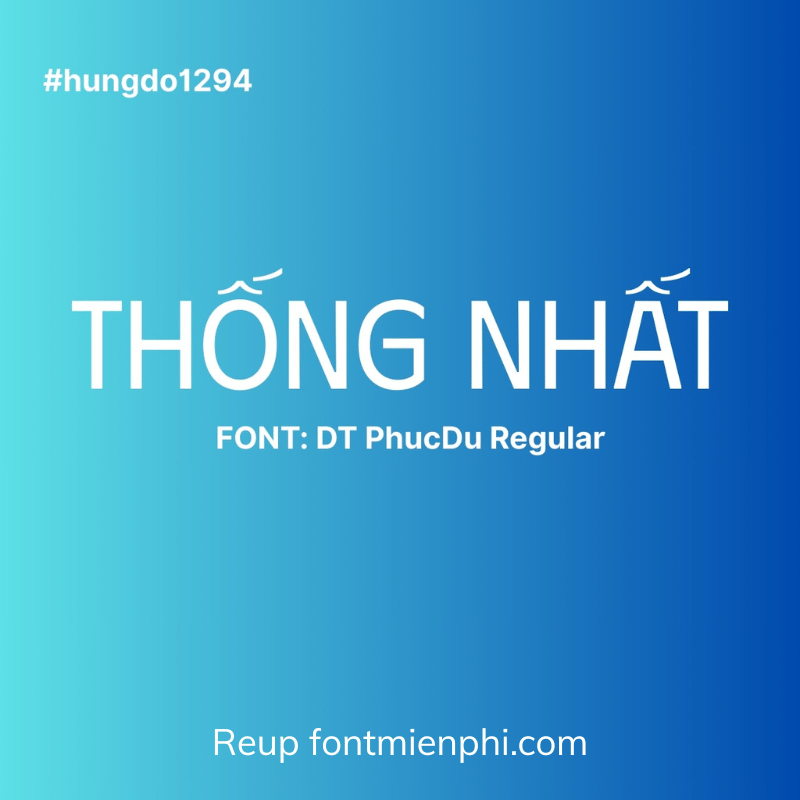
Mô tả SDT Phudu Việt Hóa – Font Đủ Bộ
Mô tả SDT Phudu Việt Hóa – Font Đủ Bộ, Chuẩn SEO
Giới thiệu:
SDT Phudu Việt Hóa là bộ font chữ độc đáo, được thiết kế dành riêng cho người dùng tiếng Việt. Với kiểu chữ sáng tạo, đầy phong cách, SDT Phudu mang đến trải nghiệm thiết kế ấn tượng, phù hợp với nhiều dự án từ in ấn, quảng cáo đến đồ họa kỹ thuật số.
Đặc điểm nổi bật Mô tả SDT Phudu Việt Hóa – Font Đủ Bộ :
• Font đủ bộ: Hỗ trợ đầy đủ bảng mã Unicode, bao gồm dấu tiếng Việt (Vietglyph), đảm bảo hiển thị sắc nét trên mọi nền tảng.
• Thiết kế độc quyền: Nét chữ mềm mại, hiện đại, phù hợp với thiết kế logo, banner, poster và các ấn phẩm nghệ thuật.
Ứng dụng:
SDT Phudu Việt Hóa là lựa chọn hoàn hảo cho designer, marketer, người làm content muốn tạo điểm nhấn cho sản phẩm của mình. Font chữ này đặc biệt phù hợp với thiết kế thời trang, nhãn hiệu, và các dự án sáng tạo cá tính.
Kết luận Mô tả SDT Phudu Việt Hóa – Font Đủ Bộ:
Với phong cách độc đáo và khả năng tương thích cao, SDT Phudu Việt Hóa là giải pháp font chữ lý tưởng cho mọi dự án sáng tạo. Tải ngay để khám phá sự khác biệt!